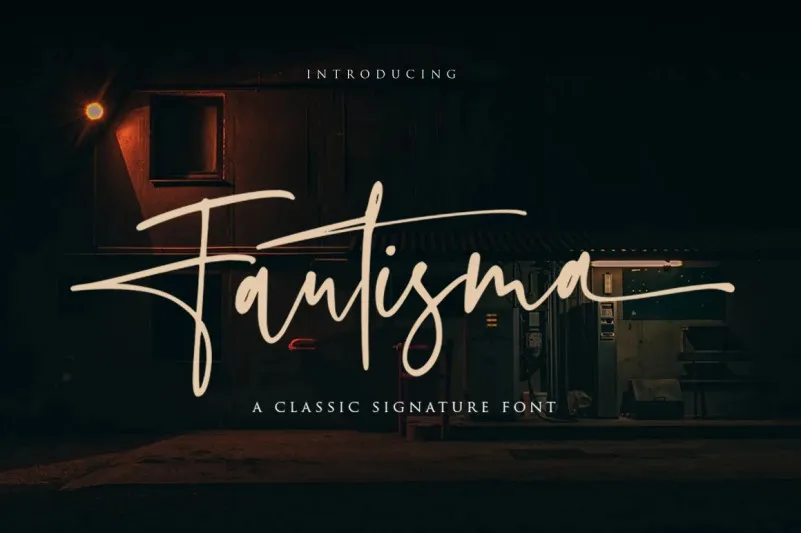
Fautisma Font – Download Grátis
Esta é uma fonte script feita à mão pela Vultype Co., com linhas limpas e caracteres divertidos. É projetada para atender tanto aqueles buscando fontes para Instagram quanto os amantes de scripts para trabalhos DIY, transformando qualquer ideia criativa em verdadeiras obras de arte. Com as características OpenType de ligação, essa fonte oferece um toque extra de originalidade e imaginação, tornando-a perfeita para quem busca diversificar seus projetos gráficos. Seja você designer web, ilustrador ou fotógrafo, este é o tipo de fonte que dará vida a suas ideias mais imaginativas. Não perca essa oportunidade de adicionar personalidade e sofisticação à sua próxima criação visual.